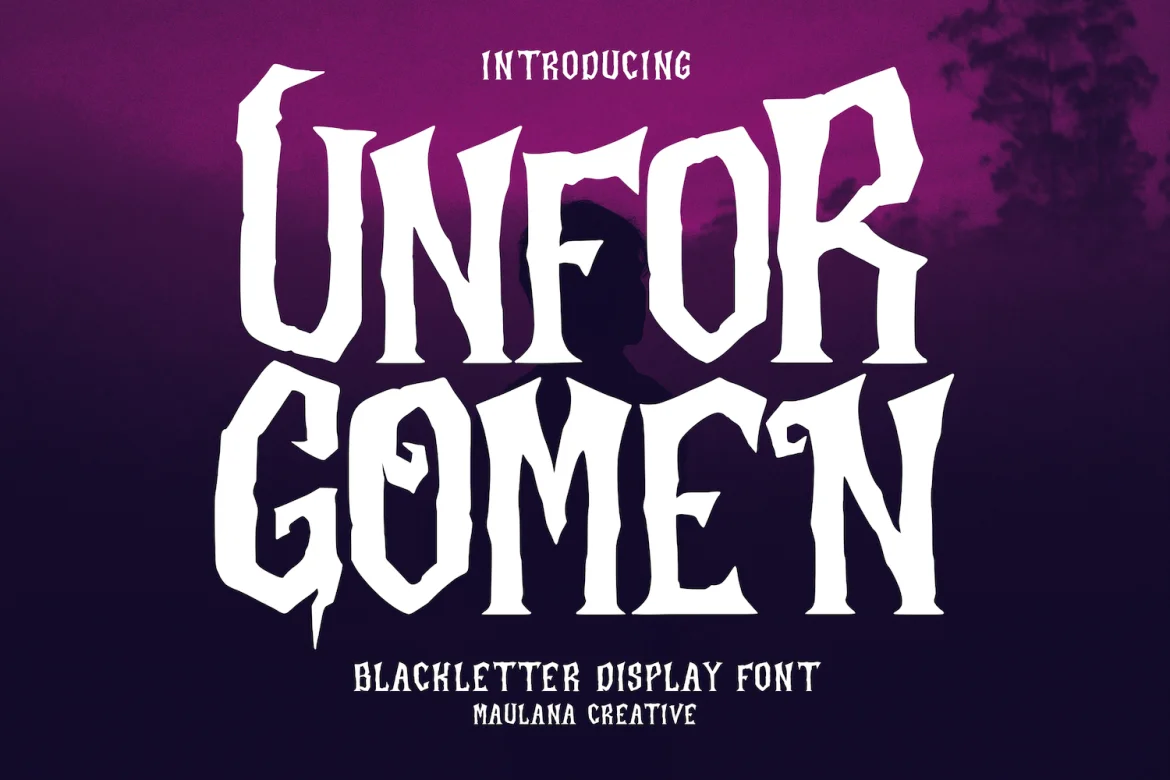
دانلود فونت Unforgomen Blackletter Display Font
Unforgomen یک قلم سریف نمایشگر کلاسیک است. با کنتراست کم کنتراست متوسط، شخصیت سرگرم کننده با کمی رباط و متناوب. تا یک کار خلاقانه اضافی به شما بدهد. فونت Unforgomen از بیش از 100 زبان چند زبانه پشتیبانی می کند. این فونت برای طراحی لوگو، رسانه های اجتماعی، عنوان فیلم، عنوان کتاب، یک متن کوتاه حتی یک حرف متن طولانی و برای فونت متن ثانویه با اسکریپت یا سریف خوب است. با فونت Unforgomen یک کار خیره کننده بسازید.